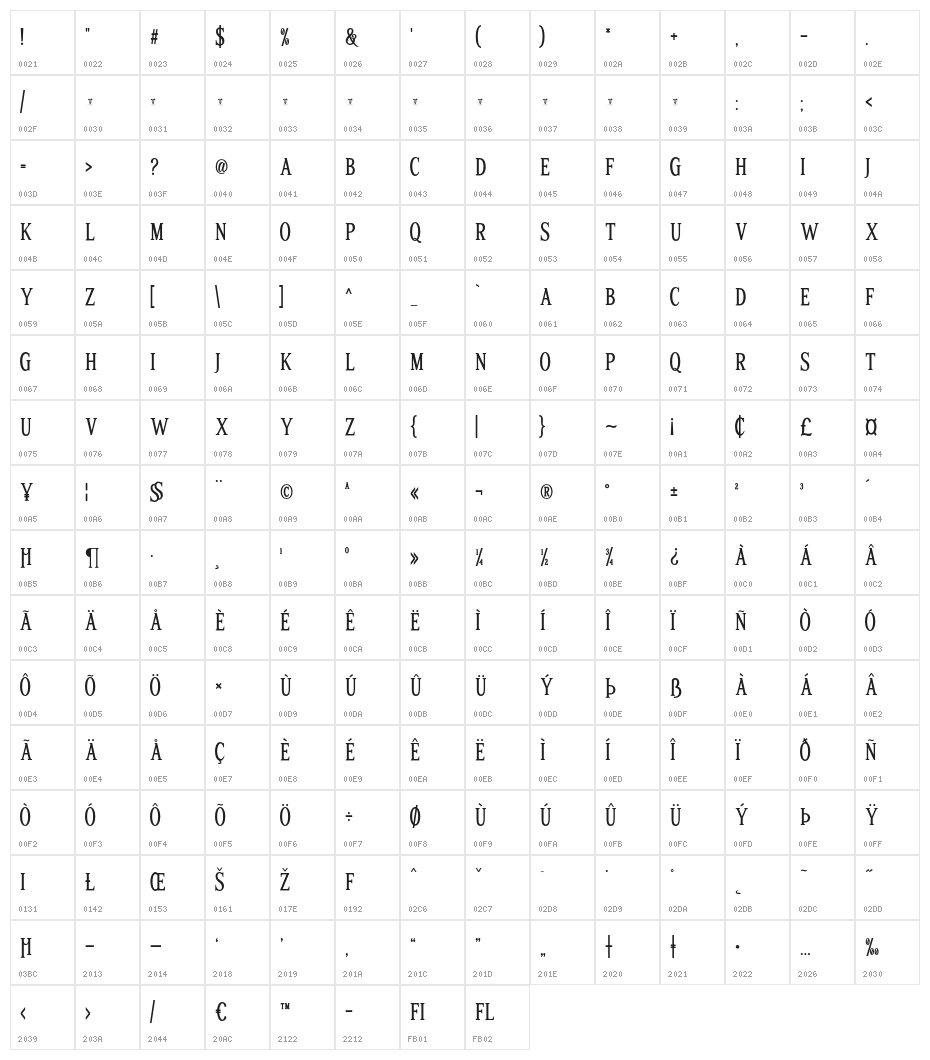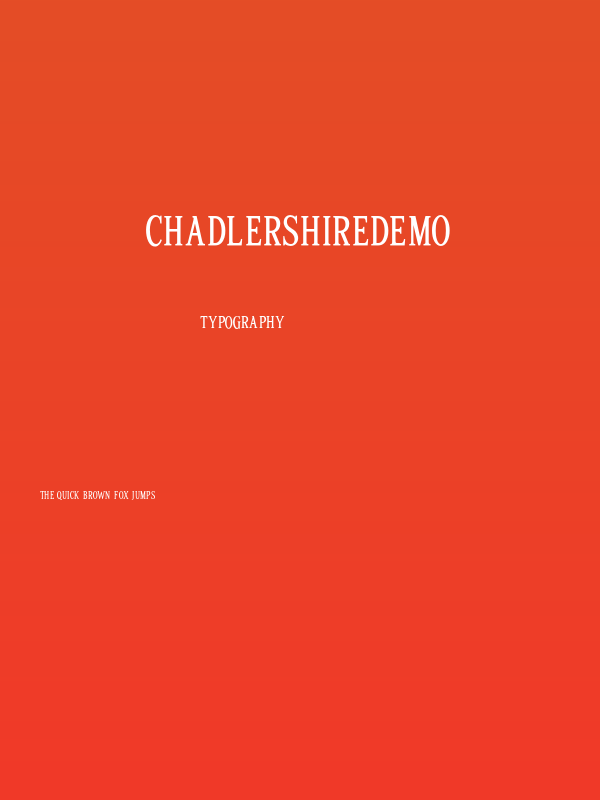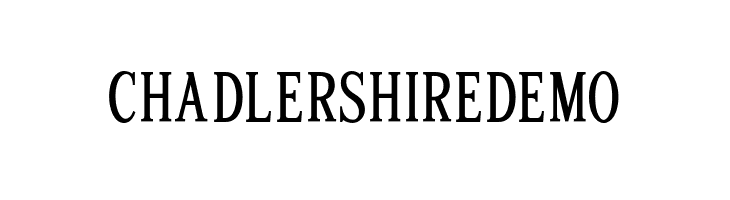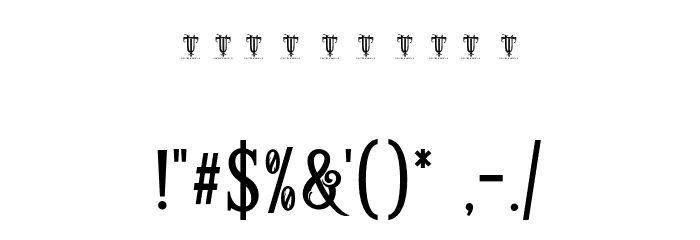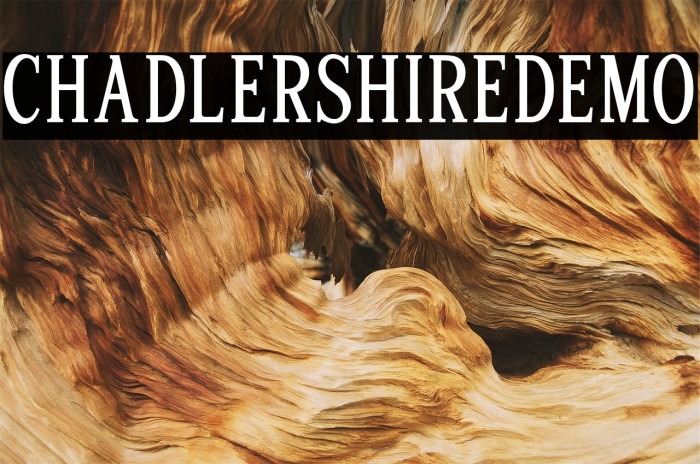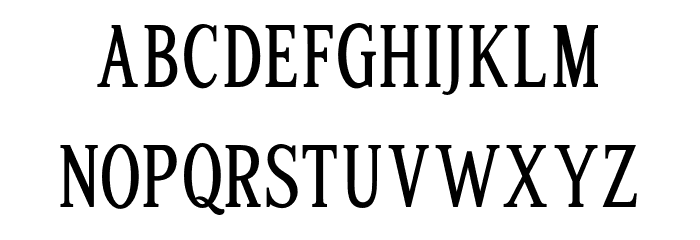
Chadlershiredemo Font
✎ Serif
| Progetti proposti | Ideal for book covers, formal invitations, corporate branding, and editorial design. |
| Autore | Fonts by scratchones |